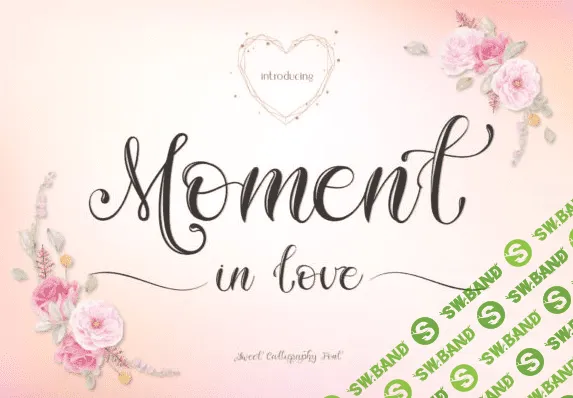
Название: Moment Font
Романтичный и милый рукописный шрифт.
Он прекрасно смотрится на различных дизайнах, требующих индивидуального стиля, таких как свадебные приглашения, открытки с благодарностью, свадьбы, поздравительные открытки, логотипы и так далее.